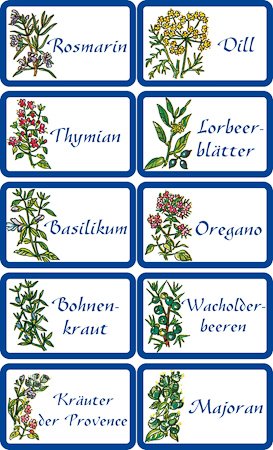
[Mitglied mätz…] Geschrieben März 26, 2014 Teilen Geschrieben März 26, 2014 hallo leute! ich muss bitte unbedingt wissen, welche schriftart bei meinen gewürzetiketten verwendet wurde. Ich will noch gewürze hinzufügen und die etiketten dafür selber drucken, da ich leider echt pedantisch bin, muss es unbedingt die selbe schriftart sein! Ich hab die schriftart vor jahren schon mal runtergeladen, es gibt sie also, leider hab ich dann den pc neu aufgesetzt und weiß beim besten willen nicht, wie die schrift hieß... bitte helft mir, ich träume schon von buchstaben vom ganzen suchen... die etiketten gibts unter anderem auf amazon: http://ecx.images-amazon.com/images/I/51kFnb+rziL.jpg "Whatthefont" und "Whatfontis" haben mich leider auch nicht weiter gebracht. ich hoffe, jemand kann mir helfen, danke jedenfalls mal fürs versuchen lg mätzchen Link zu diesem Kommentar
[Mitglied 887c…] Geschrieben März 26, 2014 Teilen Geschrieben März 26, 2014 Vodevile von Paratype Link zu diesem Kommentar
Beste Antwort Ralf Herrmann Geschrieben März 26, 2014 Beste Antwort Teilen Geschrieben März 26, 2014 Wie im Text des Links zu lesen, auch unter dem Original-Namen Gazelle zu bekommen. Der russische Ausbau der Schrift wird es wahrscheinlich nicht gewesen sein, der da für die deutschen Etiketten benutzt wurde. http://www.dafont.com/gazelleflf.font 1 Link zu diesem Kommentar
[Mitglied 887c…] Geschrieben März 26, 2014 Teilen Geschrieben März 26, 2014 Stimmt. Ich hatte sie nur schnell bei wtf gesucht. Aber vielleicht will er ja борщ einmachen, dann hätte er schon mal den richtigen Font dazu Link zu diesem Kommentar
[Mitglied boer…] Geschrieben März 27, 2014 Teilen Geschrieben März 27, 2014 Irre ich mich, oder gab es diese Schrift nicht auchals Bleisatzversion von Berthold? Link zu diesem Kommentar